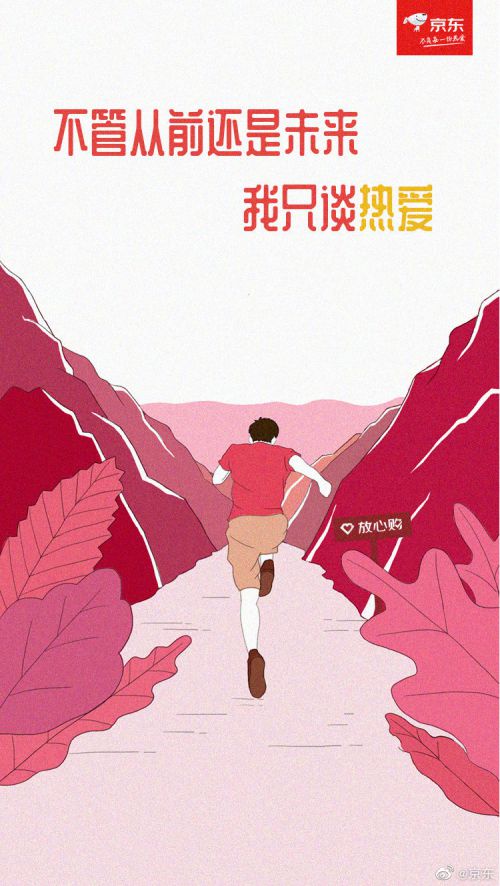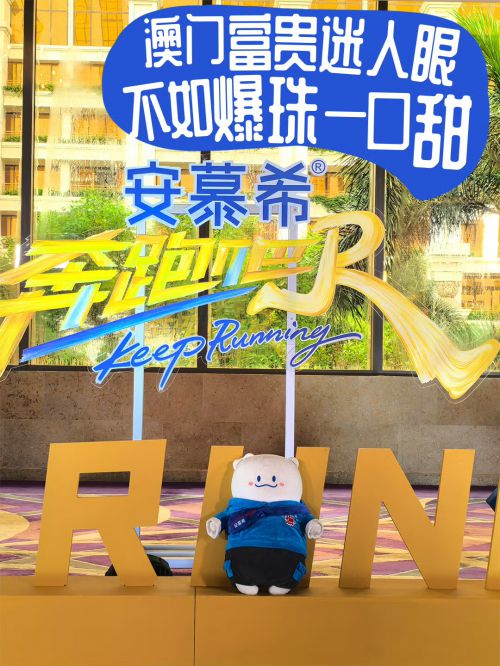
站酷庆科黄油体
字库品牌: 站酷字体
站酷庆科黄油体是由站酷字体推出的创意简体中文字体,以现代简约风格为核心,兼具端庄优雅的视觉气质。字体采用方正结构设计,字体重心居中,中宫松紧适中,整体呈现稳定平衡的视觉效果。笔画以粗线条为基调,末端融入圆润处理,搭配均匀的粗细分布与圆头笔型设计,既保留了几何图形的利落感,又通过断开式笔画连接增添灵动气息,恰似黄油般柔滑醇厚的质感。 站酷庆科黄油体支持免费商用授权,常规字符集覆盖日常设计需求,适用于品牌LOGO、包装设计、社交媒体配图、电商Banner等多元场景。其将可爱与雅致巧妙融合的设计语言,既能传递活泼亲和力,又不失现代设计的高级感,为创意作品注入独特视觉魅力。